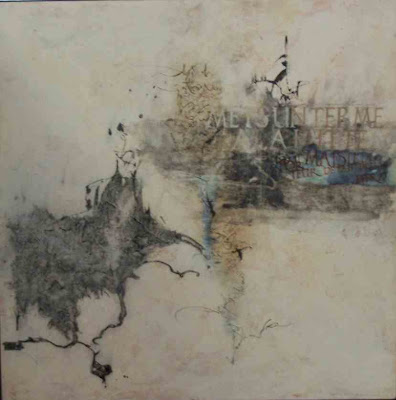
Format : 50x50Technique : médium enduit, pigments, encre acrylique noire, collage et impression de papier structuré (le papier, assez épais, contient des fils).
Ecritures : capitale à la plume et au pinceau, interprétation gestuelle de cursive romaine.
Ce tableau a été réalisé lors de l'été 2008 pendant un stage au thème libre dans la chaleur du sud ouest. C'est très formateur de discuter ses options, ses choix avec un oeil professionnel qui conseille, et laisse en même temps l'évolution personnelle se faire.
Il reprend la toute fin de l'Odyssée, alors qu' Ulysse va libérer sa fureur vengeresse sur les prétendants. Athéna intervient et impose la paix. La capitale au pinceau par sa forme imposante porte la voix de la déesse qui fait force de loi. Et en effet, malgré les ressentiments, au-delà de la réparation, il faut bien à un moment avoir la force de faire la paix, de se civiliser. Le tableau oppose ainsi des teintes claires, à la fois cadre de l'action et visage de la paix aux tracés et zones sombres suggérant mouvement et violence.